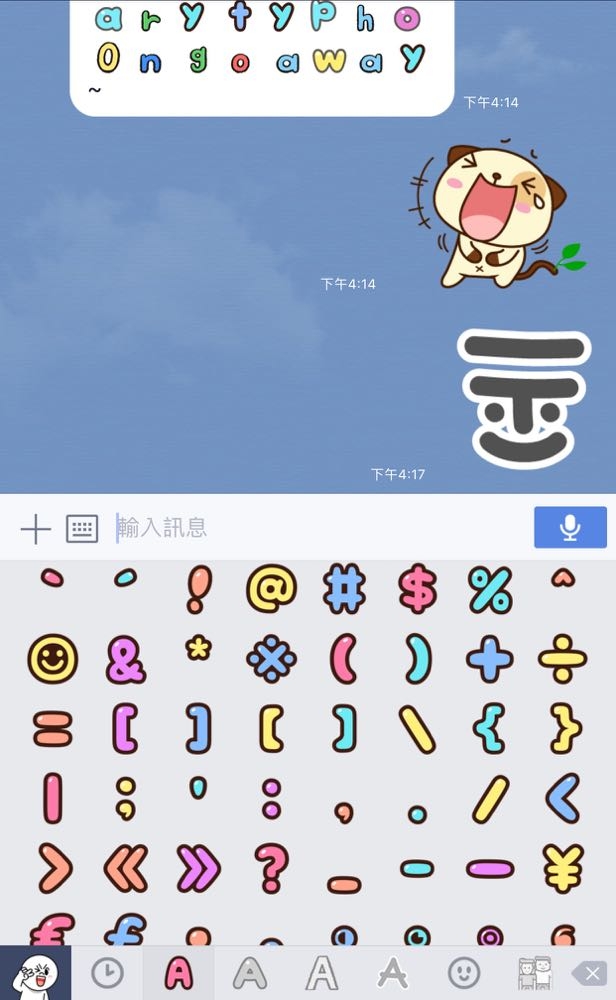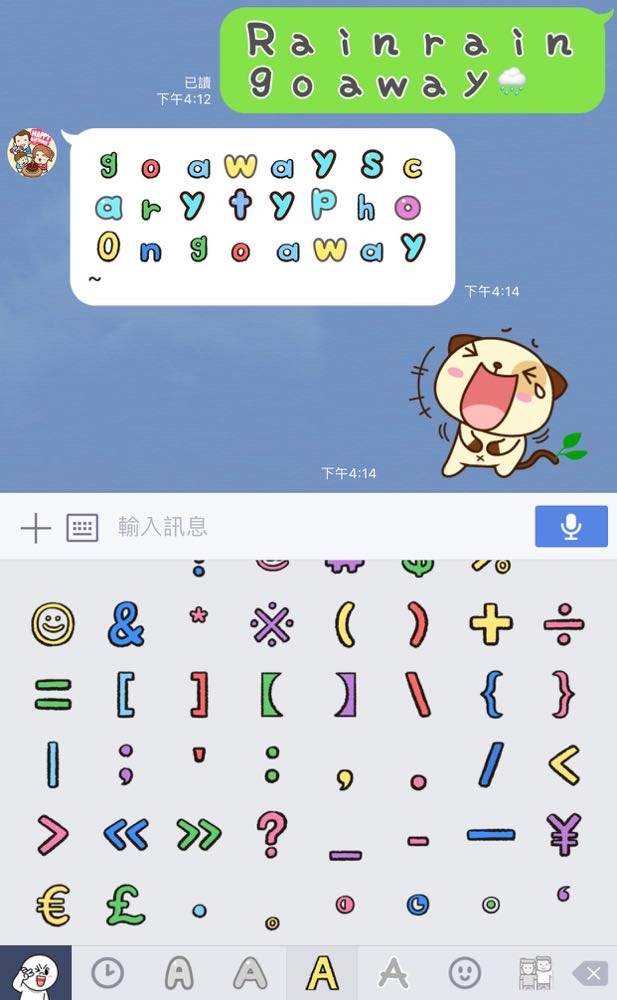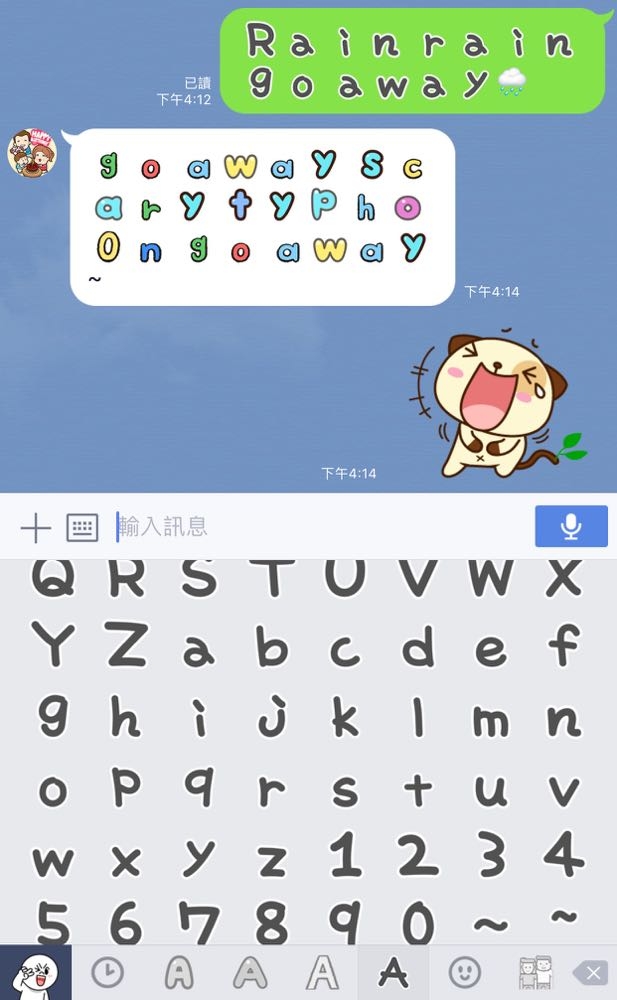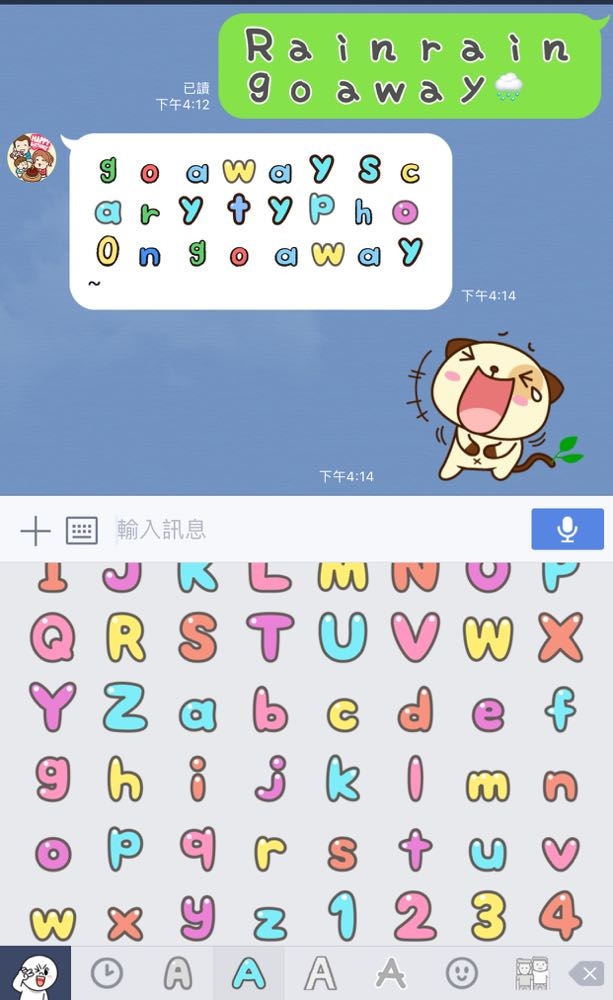
LINE 不只貼圖可愛 連字型都好繽紛!
LINE 怎麼越來越可愛了!現在 Line 的貼圖中不只有內建的可愛表情,還直接為大家帶來 4 種英文字與標點符號可愛圖示!
LINE 的用戶只要更新到新版的 LINE 之後就能發現,只要在輸入時輸入英文或是標點符號,系統便會出現多種超可愛字體選擇。而且除了在打字的時候用被動的方式來挑選,我們還可以直接點選鍵盤下方的貼圖,選擇笑臉的灰色符號,就能看見旁邊出現了四種不同的字體提供選擇。
一項以可愛貼圖深受年輕人喜愛的通訊軟體 LINE 現在一口氣推出了四種不同的新字體,是不是就連字體和那些本來看起來很普通的符號也變得相當的… LINE 了呢?!